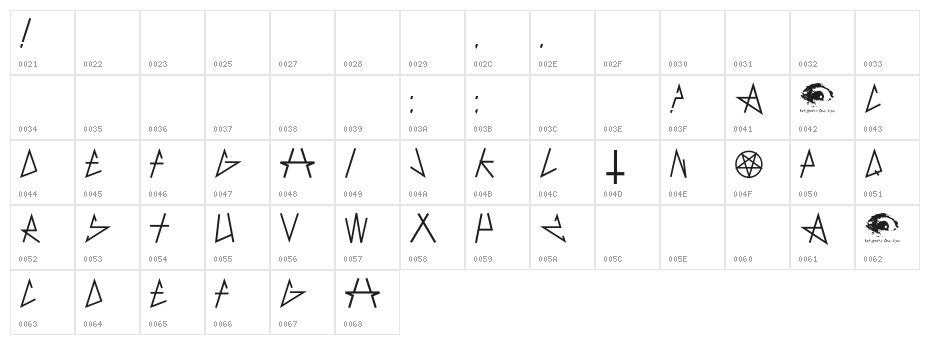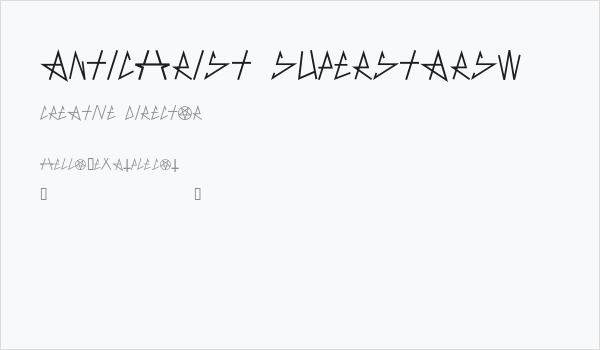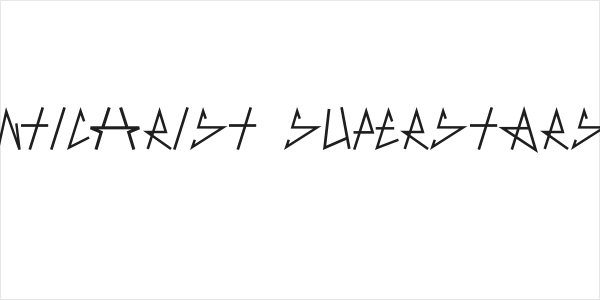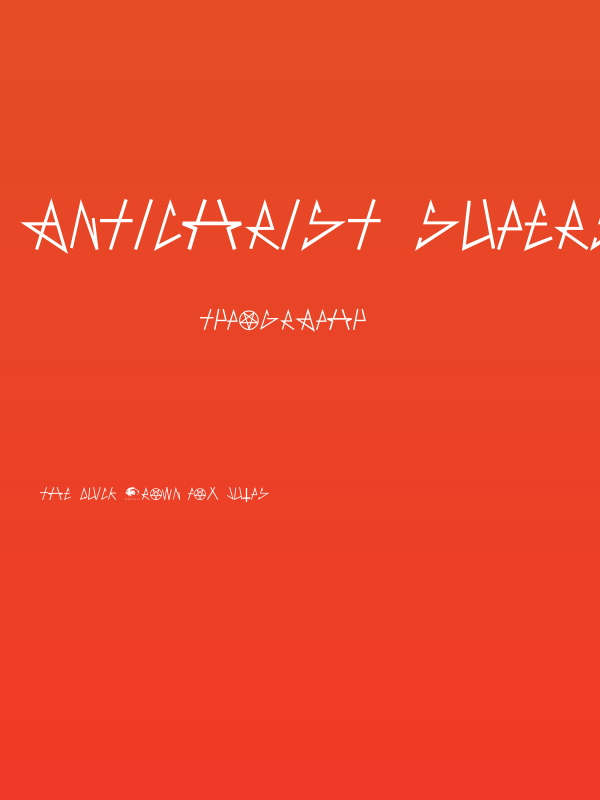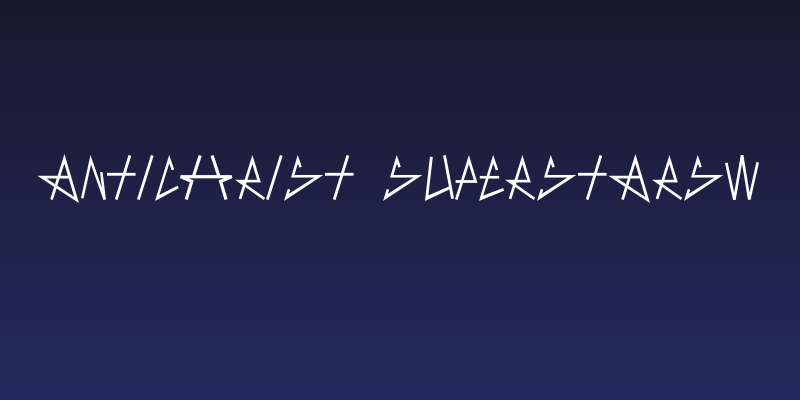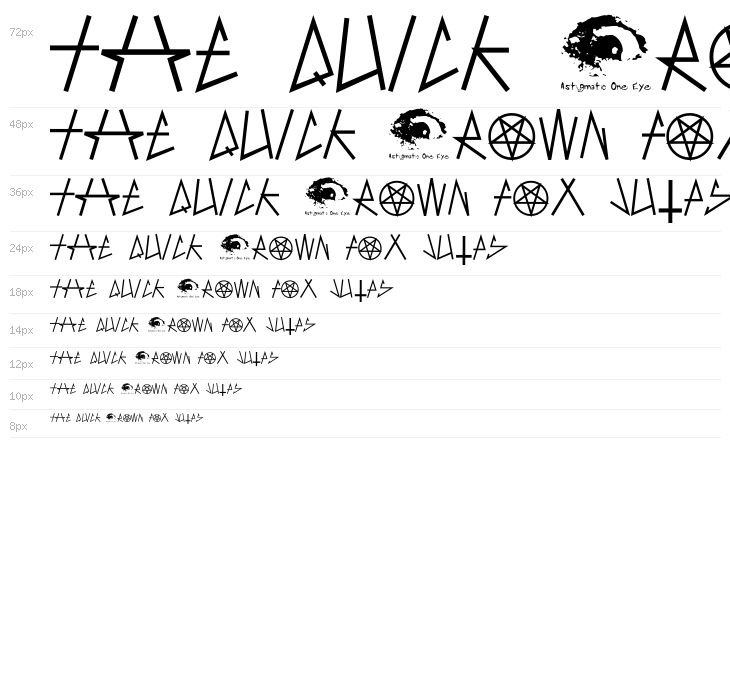
AntiChrist SuperstarSW Font
| Estilo general | Gothic, Mystical, Esoteric |
| Caso de uso | Logos, Posters, Album Covers |
| Proyectos propuestos | Ideal for album covers, horror movie posters, gothic-themed events, or any project needing a dark, mysterious vibe. |